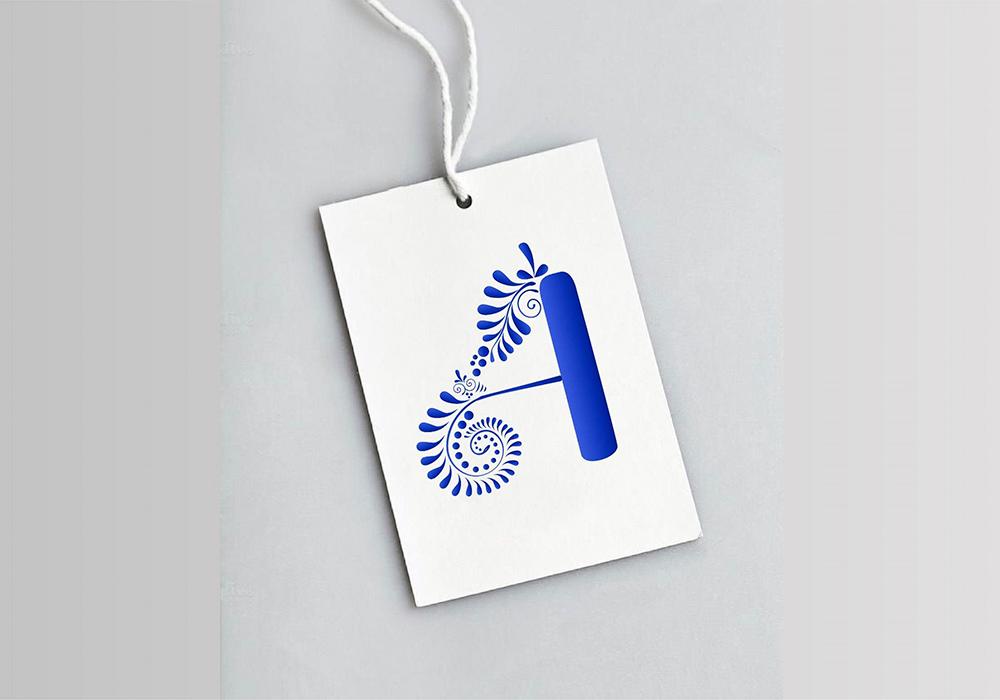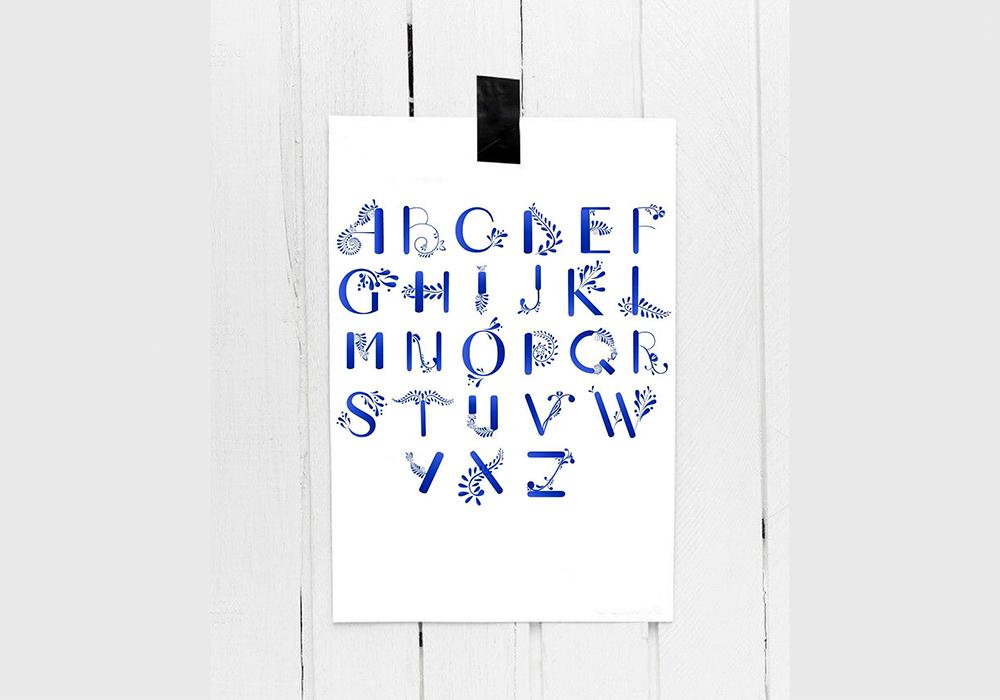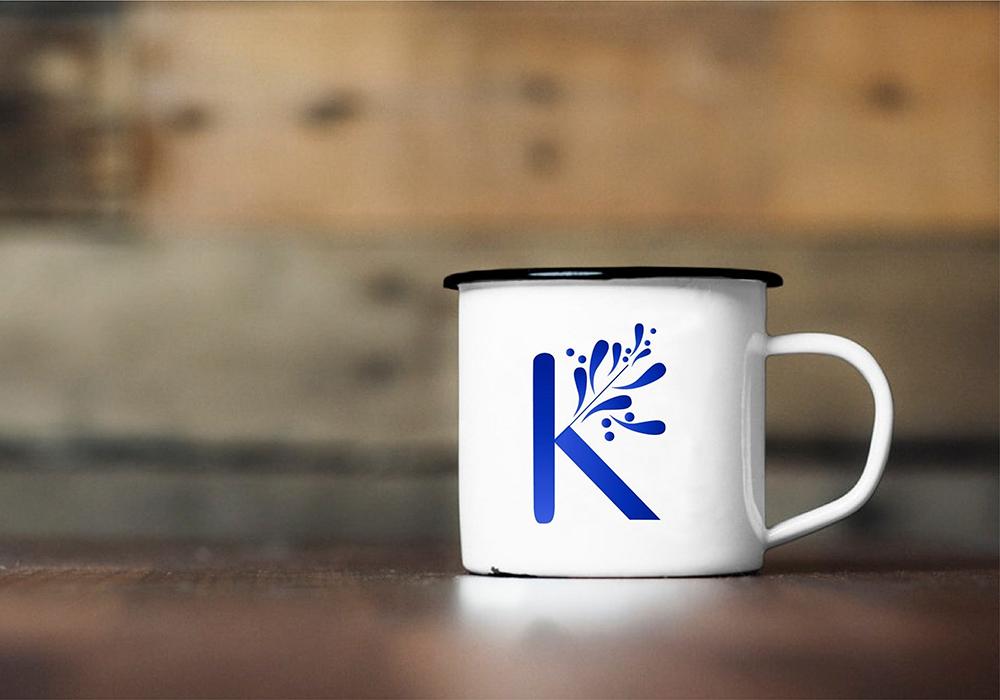
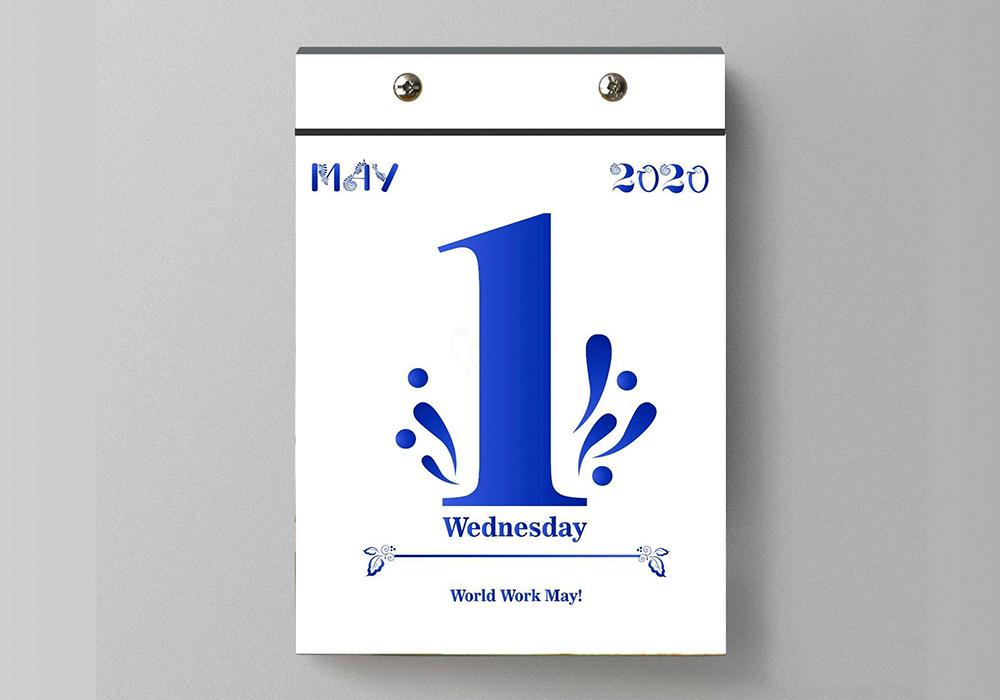
Студенты профиля «Графический дизайн» стали победителями конкурса «Гжель 2.0.».
В прошедшее воскресенье в пространстве главного цеха “Объединения Гжель” прошло образовательное мероприятие “Гжель 2.0. Вчера — сегодня — завтра”, в ходе которого были подведены итоги конкурса на создание дизайн-проекта и награждены его победители.
Конкурс “Гжель 2.0” проводился с 15 августа по 15 сентября Союзом дизайнеров России и Российским союзом туриндустрии в рамках национального проекта “Культура”. В трех номинациях — “Студенты”, “Профессионалы” и спецноминации “Артзабор” — приняли участие 80 человек.
В номинации «Студенты» лучшими были признаны пять второкурсников Института бизнеса и дизайна — Дарья Братугина, София Газиянц, Анна Кудашова, Елизавета Узлова и Мия Хагуш. Они полностью разработали шрифт, интегрировав в него узнаваемые декоративные элементы гжельской росписи. Кроме этого, авторы предложили варианты использования шрифта — к примеру, на кружках, именных карточках или в отрывном календаре.